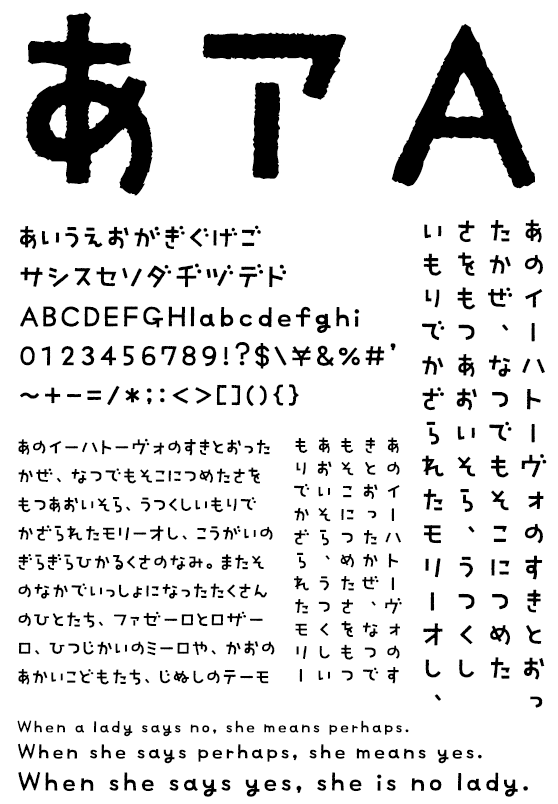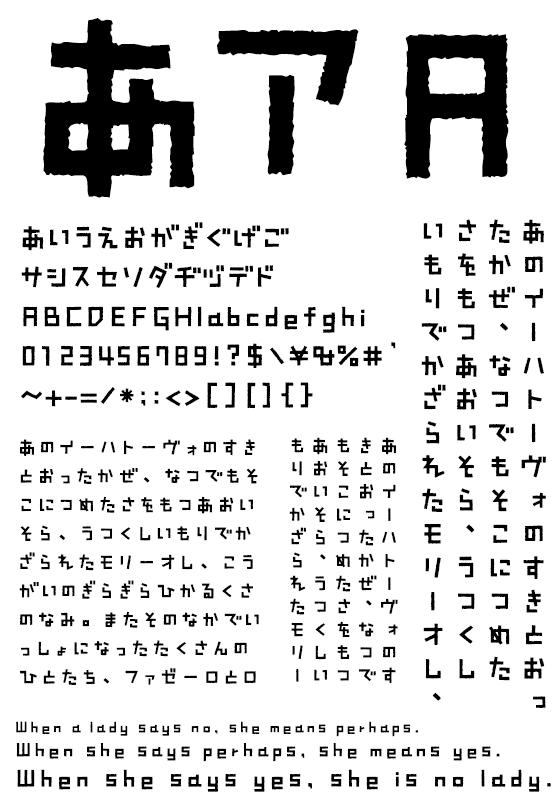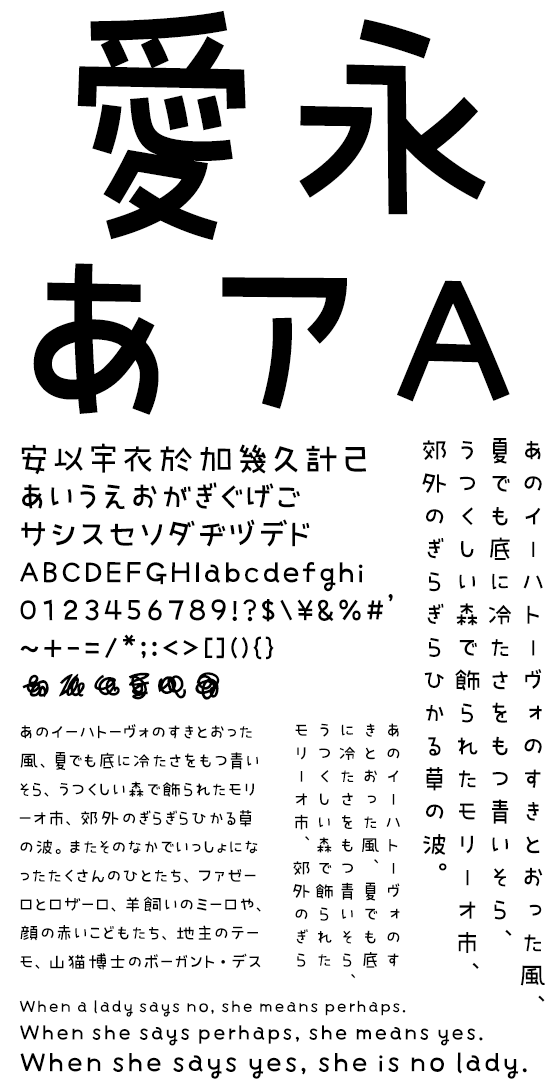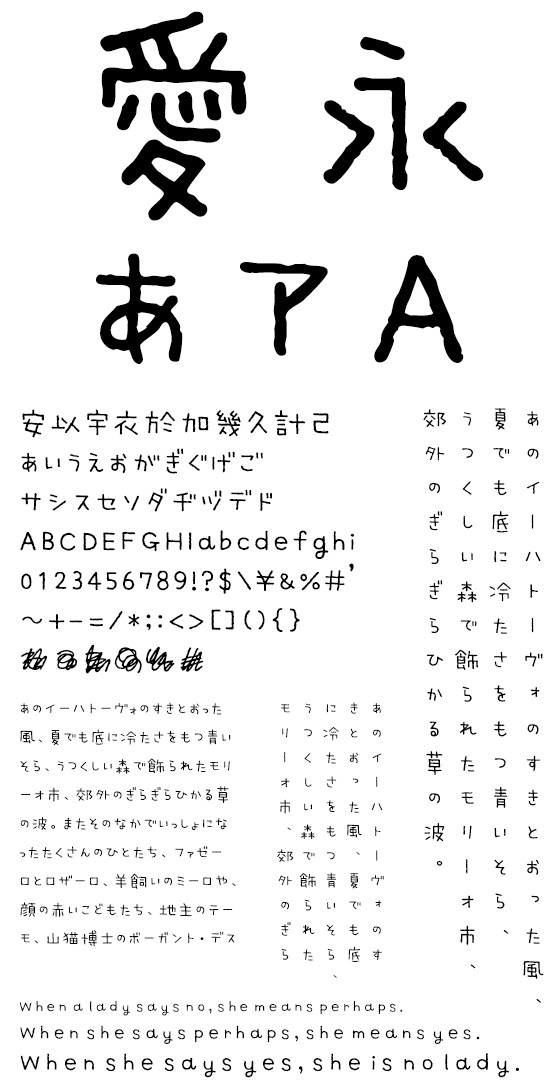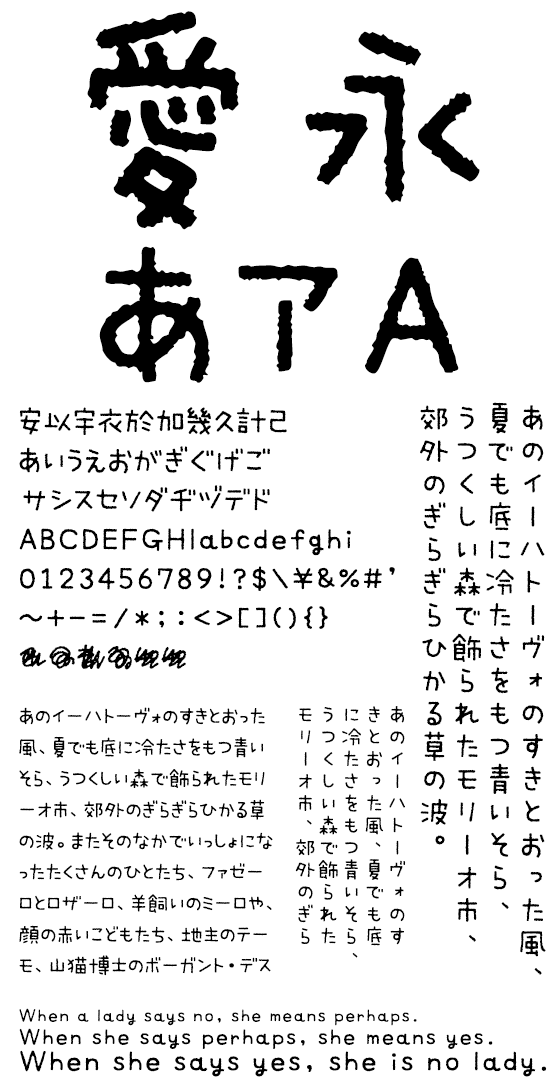
MopStudio ミウラFONTシリーズ かわいい手書き風デザイン書体
かわいい手書き風デザイン書体 MopStudio「ミウラFONT」シリーズ
MopStudioの「ミウラFONT」シリーズは、可変幅と特殊文字が特徴の手書き風デザイン書体です。手書き文字らしさを最大限に表現するため、日本語書体としては異例にも全ての文字を可変幅 (プロポーショナル) で作成した特殊なフォント。「グシャっ」とした書き直し筆跡など、オリジナルの記号も魅力です。
ミウラFONTシリーズの特徴
可変幅 (プロポーショナル) の日本語文字
通常は固定幅で作られることの多い日本語文字にも個別の文字幅を設定。画数の多い字は膨らんで、少ない字は縮んで、フォントの均一感の中に、手書きのバラバラした自由な感じを残しています。
また、一文字ひともじのデザインにも手書きの柔らかさや暖かみが出るように工夫を凝らしています。
ミウラゴチック プロポ R 文字幅サンプル
これに加えて OpenType の機能を生かしたペアの字詰め情報も持っているので、例えば「す。」などもきれいです。
タイトルやポップなどに使いやすいゴシック体をベースとしながら、本文に使いやすい手書き文字の特徴を併せ持っているので、使う場所を選びません。字形自体に強い癖がなく、タイトル・見出しから本文まで使えます。メッセージカードや店頭メニューなどにも大活躍まちがいなし!
独自デザインの特殊文字
ミウラFONTシリーズでは、一部の記号にオリジナルのデザインを採用。中でもご好評の「グシャグシャ記号」は「∈ ∋ ⊆ ⊇ ∩ ∪」などの数学記号のかわりに収録されています。
グシャグシャ消した記号も収録
ミウラLinerOtf R
ミウラ見出しLinerOtf R
ミウラAiOtf B
ミウラBlockOtf B
ミウラゴチック プロポR
ミウラLinerOtf R
ちくちくと繊細な印象の、可愛らしい人気フォントです。手で丁寧に書いたような微妙なゆらぎが特徴。手書き文字を書くように使える楽しい日本語フォントです。
ミウラ見出しLinerOtf R
滲みのようなチリチリを強調し、ミウラLinerの線を強く太めにしたフォントです。字面もミウラLinerより大きめにデザインされており、文字の大きさの変化を小さく文字間も詰め気味にして、見出しなどに使いやすく調整されています。
ミウラAiOtf B
より丸く、くっきり太く。Linerシリーズ同様、紙に書いたようなチリチリが特徴の「かな・カナ」フォントです。
※漢字や独自デザインの特殊文字(グシャグシャ記号)は収録していません。
ミウラBlockOtf B
手書きの風合いはそのままに、思い切ったシカクいデザインが個性的な「かな・カナ」フォントです。
※漢字や独自デザインの特殊文字(グシャグシャ記号)は収録していません。
ミウラゴチック プロポR
手書きっぽい柔らかさと暖かさを持ちながら、スタンダードなゴシック体のように使用できるフォント。ミウラ見出しLinerOtf R より、カチっとした角のあるタイトル用ゴシック風フォントです。